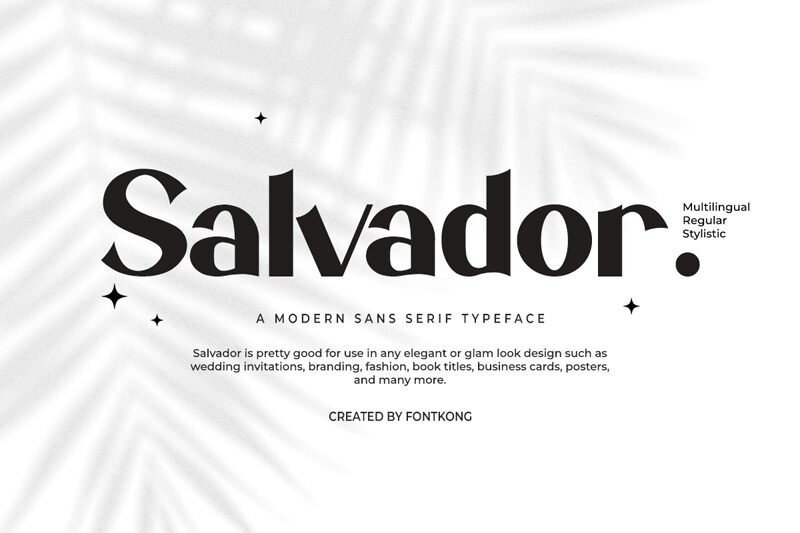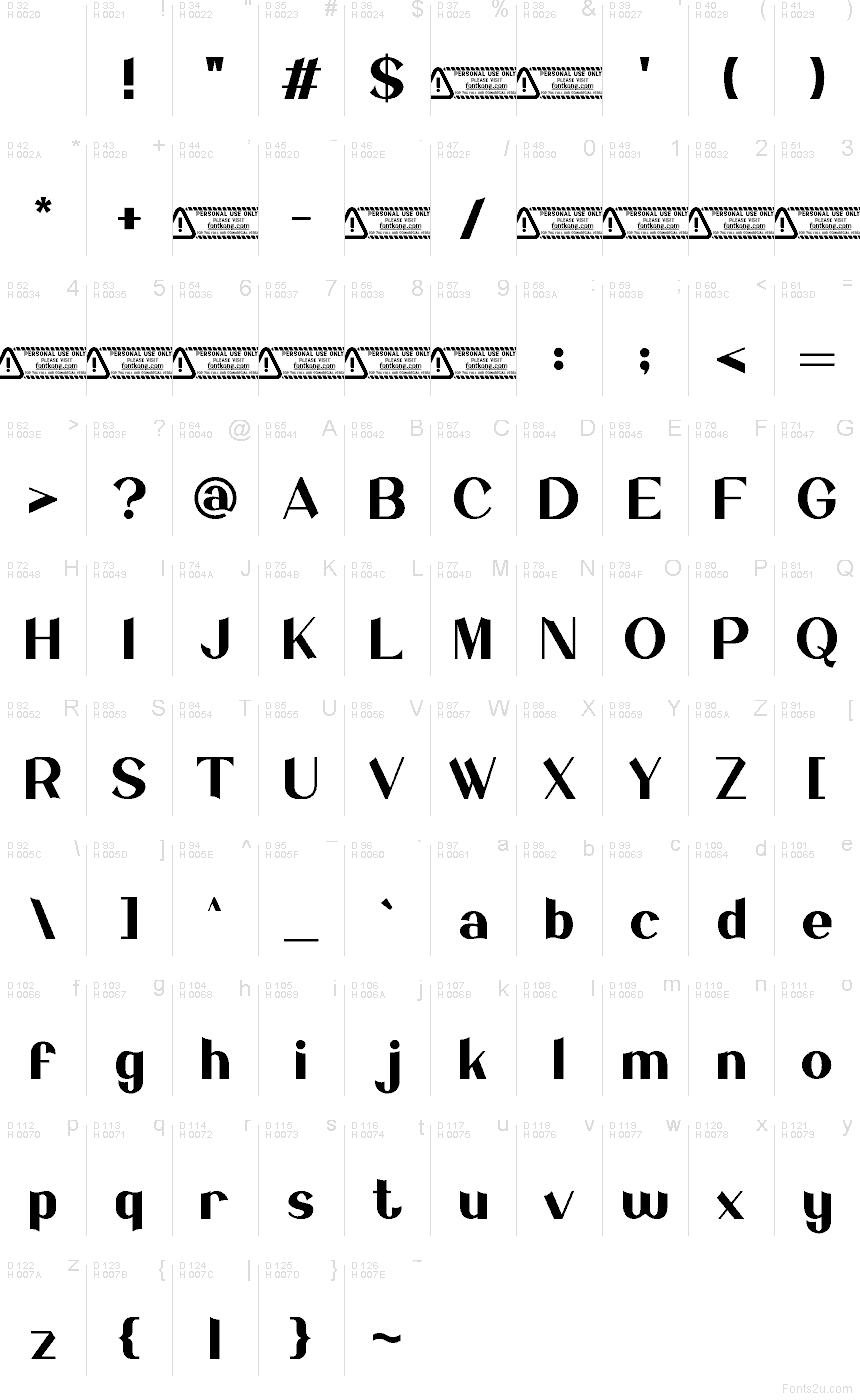
Salvador von Kong Font ist eine kostenlose, kontrastreiche Serifenschrift mit einer theatralischen Note im Old-Style-Look. Die Buchstaben verbinden weite Rundungen mit messerscharfen Verbindungen, während die spitz zulaufenden, blattartigen Serifen der Schrift eine skulpturale, literarische Präsenz verleihen, die formell wirkt, ohne steif zu sein.
Das macht sie zur idealen Wahl für Buchcover, Mode-Überschriften, Boutique-Branding, Speisekarten und Plakat-Titel, bei denen eine kostenlose Schrift das gewisse Extra an Dramatik braucht. Sie kommt vor allem in kurzen Display-Anwendungen zur Geltung – besonders bei Kopfzeilen, Titeltafeln und Monogrammen –, da ihre scharfen Details und tiefen Kurven die meiste Arbeit übernehmen.